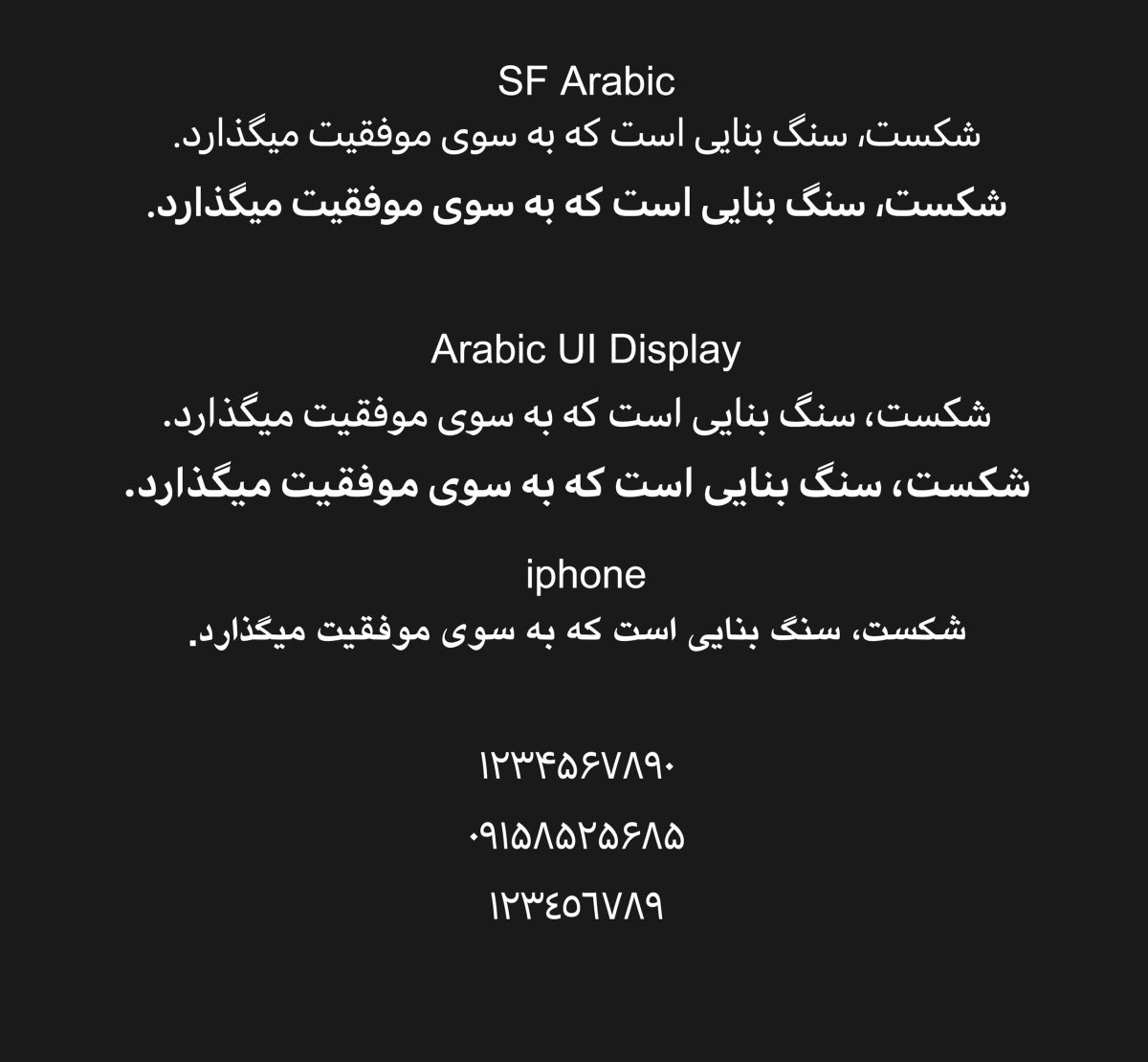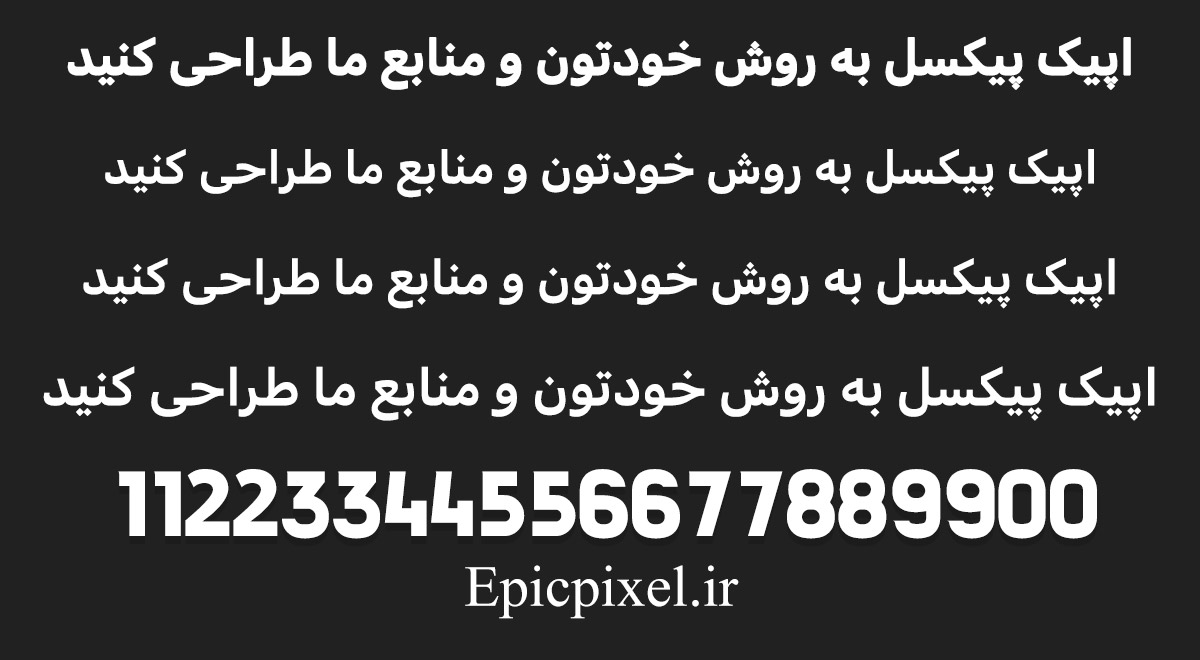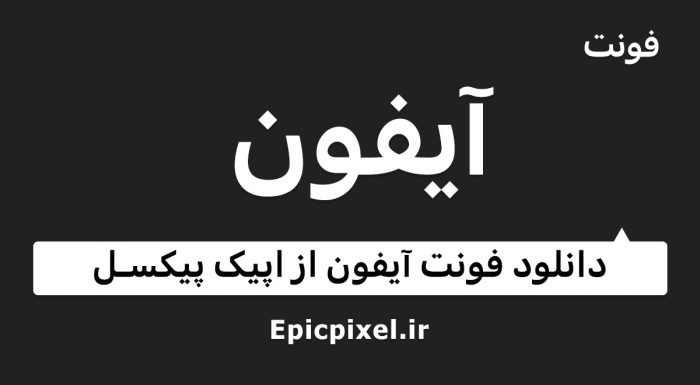
برای داشتن ظاهری یکپارچه و حرفهای در طراحیهای خود، میتوانید با دانلود رایگان فونت آیفون فارسی، از همان فونتی که در دستگاههای اپل استفاده میشود، بهرهمند شوید. این فونت با طراحی زیبا و خوانایی بالا، به متون شما هویتی مدرن و جذاب میبخشد و باعث میشود تا طراحیهایتان حرفهایتر و باکیفیتتر به نظر برسند.
این فونت ، فونت مخصوص برای اضافه کردن در گوشی IOS یا آیفون نیست .بلکه یک فونته که نوع نوشتار ( یا همون فونت) پیشفرض استفاده شده داخل گوشی های IOS 15 رو داره و شبیه به اونه . در اصل یک فونت عربی هست که فارسی سازی شده و میتونید داخل گوشی های اندرویدی مثل شیائومی / سامسونگ و… بعلاوه ویندوز و برنامه های گرافیکی مثل فتوشاپ ، اینشات ، پیکس آرت استفاده کنید و ظاهر فونت گوشی ایفون رو داشته باشید .
دانلودفونت آیفون فارسی، که به طور رسمی با نام SF Arabic (و بخشی از خانواده San Francisco) شناخته می شود، قلم استاندارد استفاده شده در محصولات شرکت اپل برای پشتیبانی از زبان های فارسی و عربی است. این قلم حرفه ای توسط اپل توسعه یافته و برای زبان های فارسی، عربی، اردو و لاتین طراحی شده و شامل حروف اختصاصی فارسی نیز می باشد. SF Arabic در ۱۰ وزن متنوع و با فرمت های گوناگونی از جمله TTF و OTF ارائه می گردد. این فونت محبوب برای طراحی وب، عناوین چاپی و متون دیجیتال مناسب است، اما نسخه اصلی آن به صورت رایگان توسط اپل عرضه نمی شود و نصب آن به عنوان فونت سیستمی در خود دستگاه های آیفون محدودیت های قابل توجهی دارد.
شناخت فونت هایی که در رابط های کاربری پرطرفدار استفاده می شوند، مانند فونت آیفون فارسی که با نام اصلی تر SF Arabic یا بخشی از خانواده San Francisco شناخته می شود، برای طراحان اهمیت دارد. این قلم زیبا توسط شرکت اپل به طور اختصاصی برای استفاده در سیستم عامل ها و محصولات خود طراحی و توسعه یافته است و ظاهری مدرن و خوانا دارد که با هویت بصری اپل همخوانی کامل دارد.
یکی از ویژگی های برجسته SF Arabic، پشتیبانی جامع آن از زبان های فارسی، عربی، اردو و لاتین است. این فونت کاربردی به طور خاص شامل حروف اختصاصی زبان فارسی نظیر گ چ پ ژ نیز می باشد که آن را برای استفاده در محتوای فارسی کاملاً بهینه و بومی سازی شده می سازد.
این فونت شگفت انگیز در ۱۰ وزن مختلف ارائه می شود که تنوع بی نظیری برای استفاده در مقاصد طراحی گوناگون فراهم می کند. این وزن ها شامل حالات Light, Regular, Medium, DemiBold, Bold, Heavy, Black, Thin, UltraLight و یک نسخه Variable (وریبل) است که امکان تنظیم دقیق ضخامت را برای طراح فراهم می آورد.
کاربردهای فونت SF Arabic در برنامه های گرافیکی
به دلیل طراحی حرفه ای، پشتیبانی از زبان های متعدد و ارائه در وزن های گوناگون، فونت آیفون فارسی (SF Arabic) ابزاری عالی برای استفاده در برنامه های طراحی گرافیکی است. طراحان در محیط ویندوز و مک می توانند از این فونت در نرم افزارهایی مانند Adobe Photoshop، Illustrator، InDesign برای خلق طرح های چاپی مانند کتاب، مجله، بروشور، یا طراحی رابط کاربری وب و اپلیکیشن بهره ببرند. همچنین، در اپلیکیشن های موبایل که از فونت های سفارشی پشتیبانی می کنند (نظیر Inshot، متن نگار، یا حتی برنامه های اپل مانند Pages و Keynote که در متن اشاره شد)، می توان از فونت آیفون برای طراحی پست ها، استوری ها و محتوای بصری جذاب در زبان های فارسی، عربی و لاتین استفاده کرد و جلوه ای شبیه به رابط کاربری آیفون به آن ها بخشید.